お守りかもエール
日本郵便の公式サイト「郵便年賀.jp」で2018年8月31日まで「お守りかもエール」特設サイトが公開された。※期間限定に現在はクローズされている。
お守りかもエールは、折るとお守りの形になるデザインテンプレートを使い、相手にエールを送れるはがき。「お守りかもエール特設サイト」では2018年8月31日まで、この「お守りかもエール」を作ることができる。デザインできるテンプレートは、シンプルなお守りの形として10種類、ユニフォームのお守りの形として6種類各10色が用意された。また、「お守りかもエール」の作成やデザインテンプレートのダウンロードは全て無料で利用できる仕組み。
「お守りかもエール特設サイト」でDynaFontサーバー用フォントライセンスが採用
「お守りかもエール特設サイト」でDynaFontサーバー用フォントライセンスが採用され、お守りかもエールで使用できる文字としてダイナフォント「娥眉明朝体W5」が採用されている。その他、お守りかもエール特設サイトでは「平成ゴシック体W5」「綜藝体W9」の2書体も採用された。
ダイナフォント娥眉明朝体W5
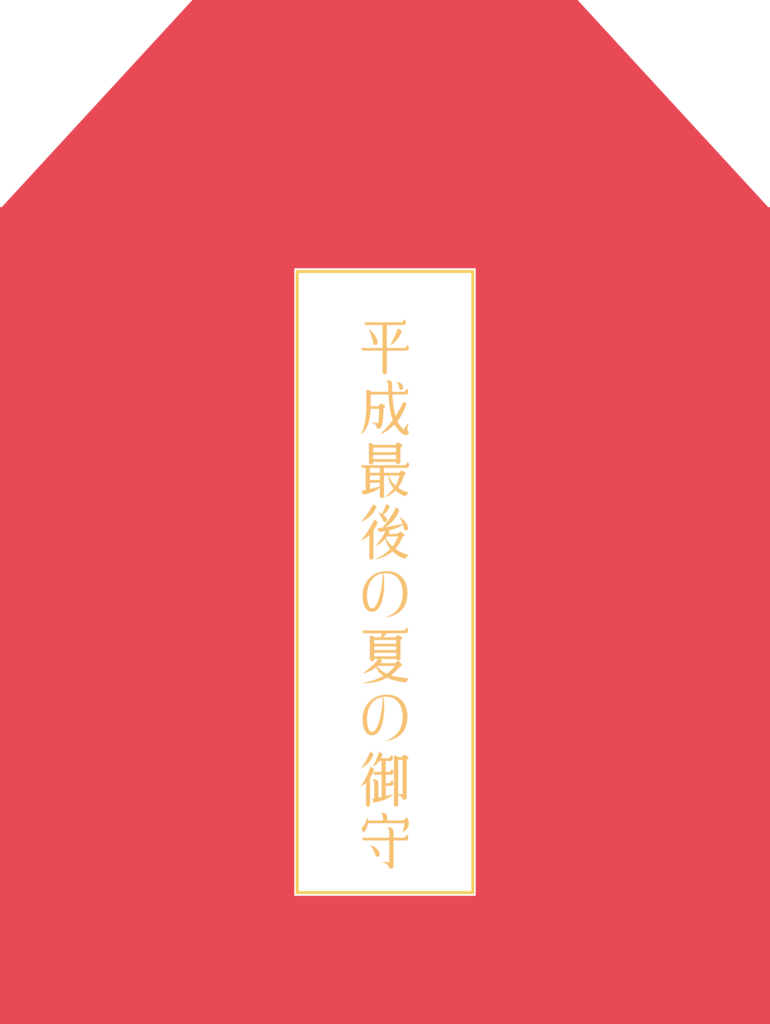
細長く弧を描いた眉の形をイメージしたストロークから洗練された女性の柔らかさや優しさを表現した明朝体。
ダイナフォント平成ゴシック体W5
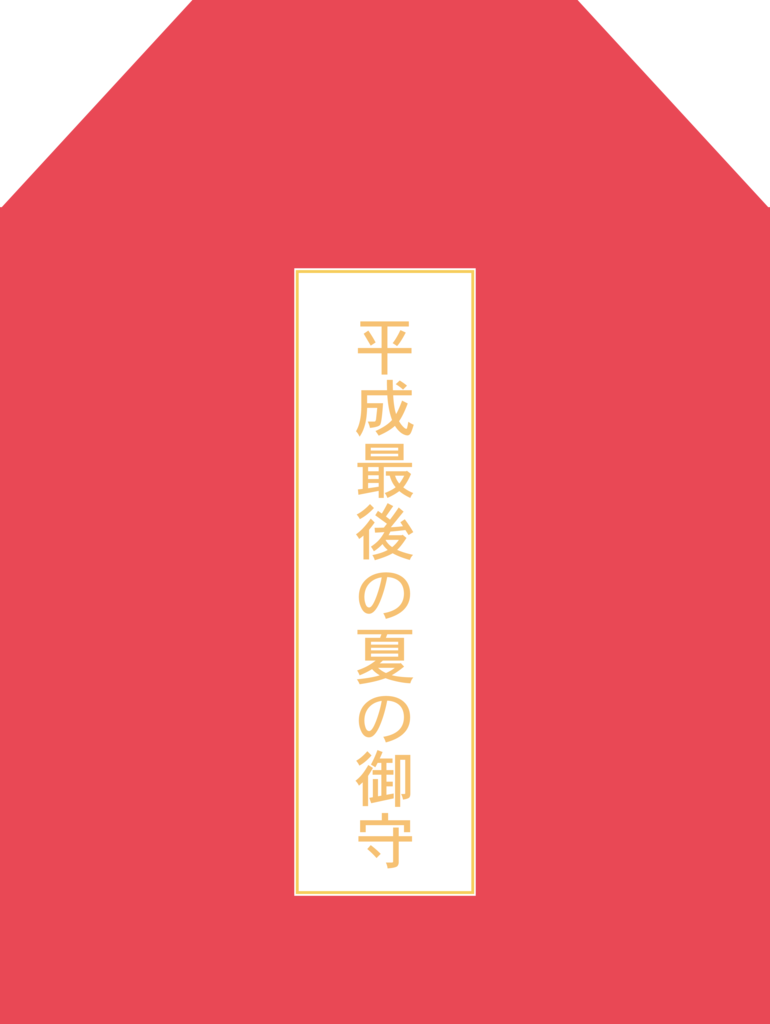
明朝体の縦画の起筆と横画の収筆の三角形を無くし、ストロークを分かりやすく調整しているゴシック体。
ダイナフォント綜藝体W9
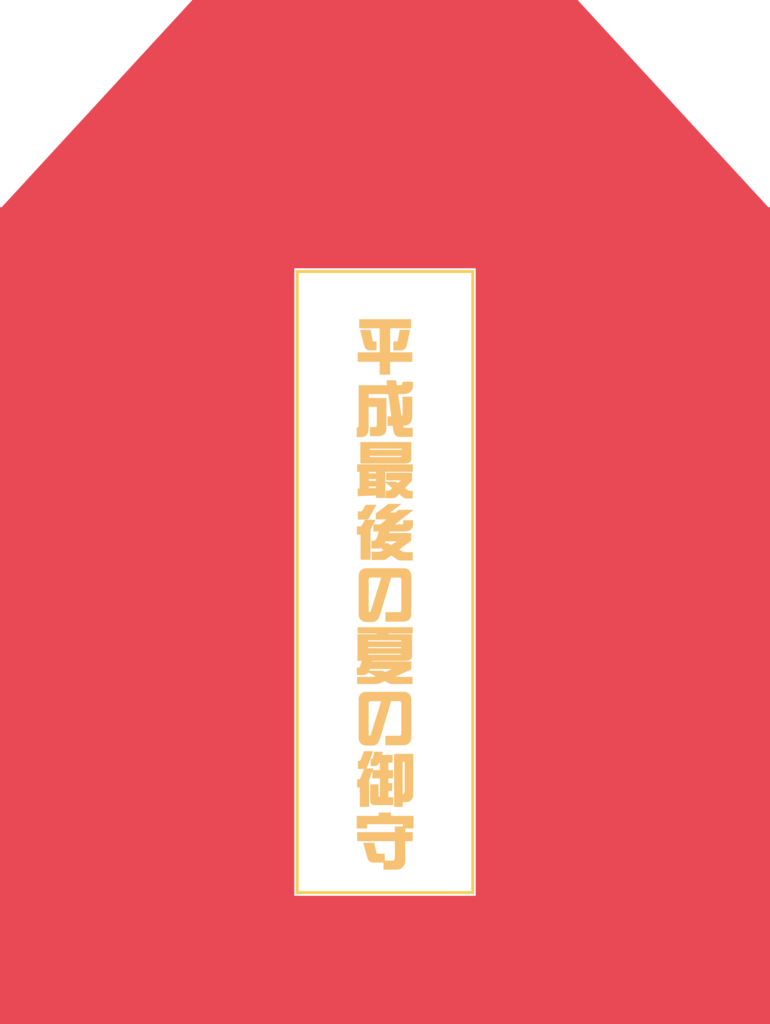
通常のゴシック体よりも太く正方な字形を採用し、1文字の中に生じる余白部分を均等化して、まっすぐ伸びた線の曲がりやハネの先端部分をややカーブさせたデザイン書体。